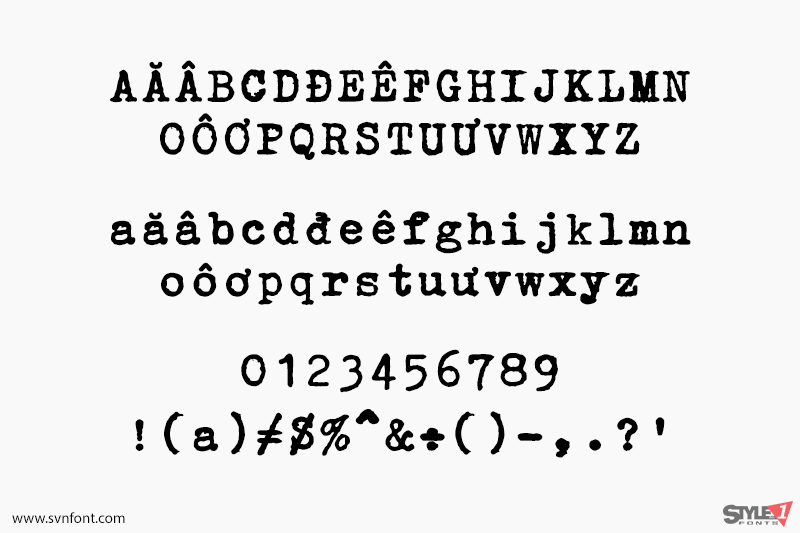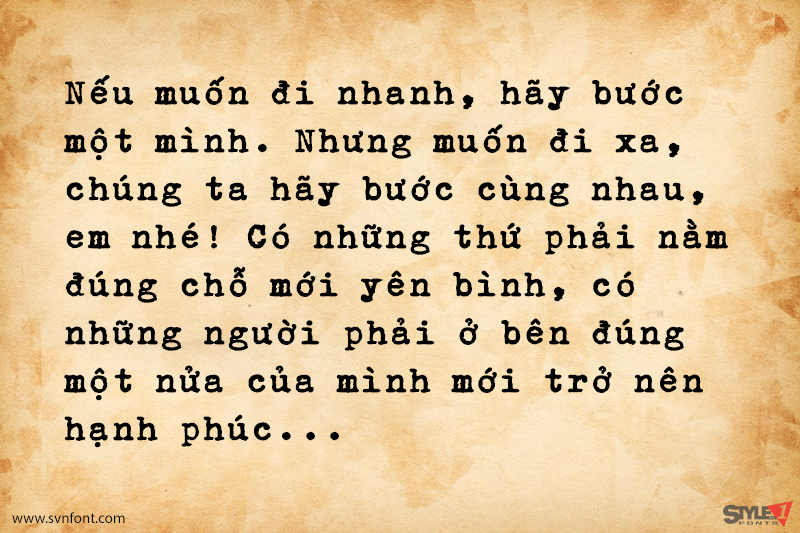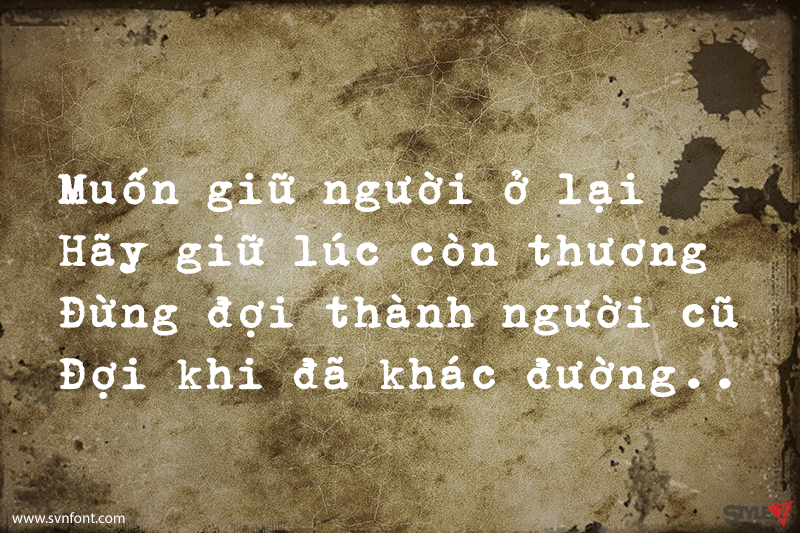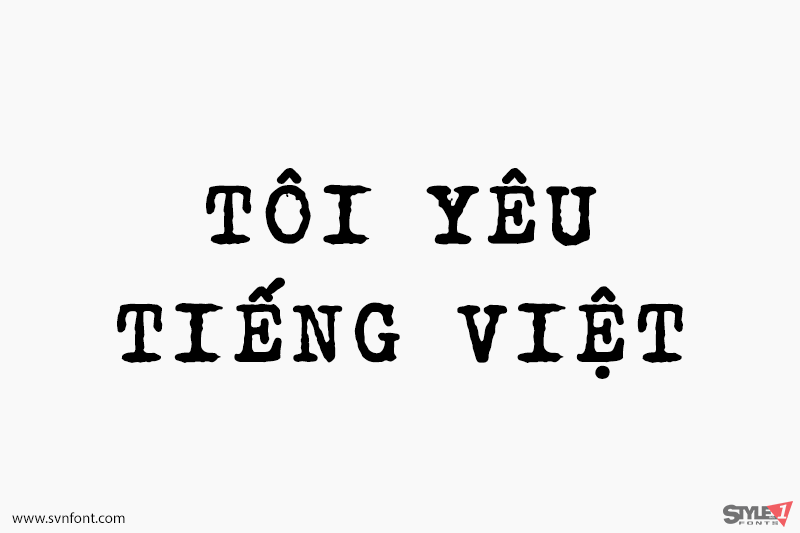
Erika Ormig là một font chữ dạng máy đánh chữ kiểu cũ, với thiết kế mô phỏng độ nhòe của mực in tạo phong cách cổ điển cho font chữ. Font thích hợp cho các thiết kế cũ.
Nhà thiết kế: Peter Wiegel